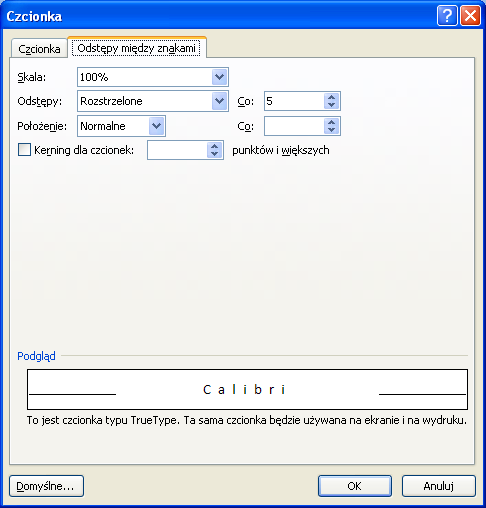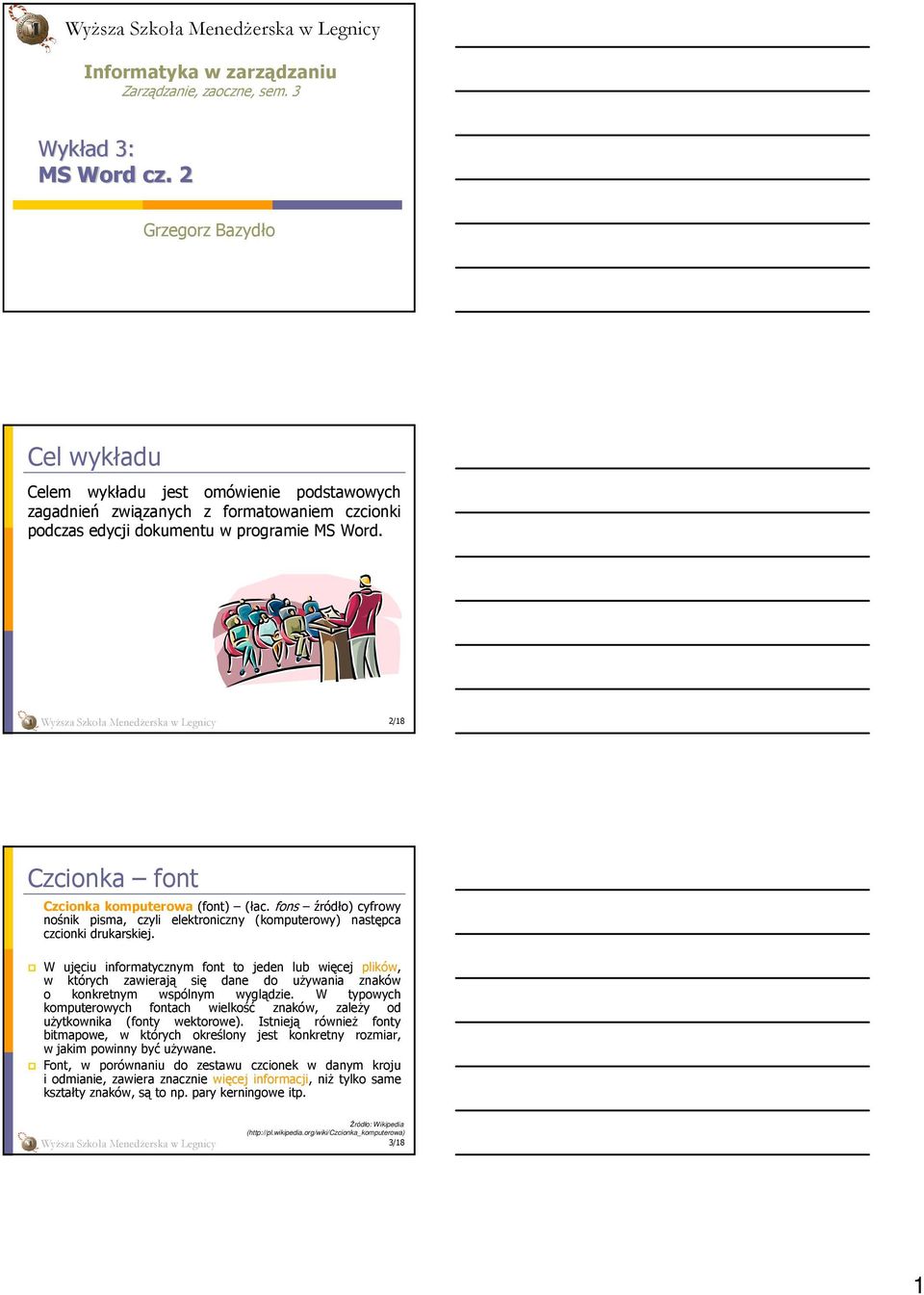
1 WyŜsza Szkoła MenedŜerska w Legnicy Informatyka w zarządzaniu Zarządzanie, zaoczne, sem. 3 Wykład 3: MS Word cz. 2 Grzegorz Bazydło Cel wykładu Celem wykładu jest omówienie podstawowych zagadnień związanych z formatowaniem czcionki podczas edycji dokumentu w programie MS Word. WyŜsza Szkoła MenedŜerska w Legnicy 2/18 Czcionka font Czcionka komputerowa (font) (łac. fons źródło) cyfrowy nośnik pisma, czyli elektroniczny (komputerowy) następca czcionki drukarskiej. W ujęciu informatycznym font to jeden lub więcej plików, w których zawierają się dane do uŝywania znaków o konkretnym wspólnym wyglądzie. W typowych komputerowych fontach wielkość znaków, zaleŝy od uŝytkownika (fonty wektorowe). Istnieją równieŝ fonty bitmapowe, w których określony jest konkretny rozmiar, w jakim powinny być uŝywane. Font, w porównaniu do zestawu czcionek w danym kroju i odmianie, zawiera znacznie więcej informacji, niŝ tylko same kształty znaków, są to np. pary kerningowe itp. Źródło: Wikipedia ( WyŜsza Szkoła MenedŜerska w Legnicy 3/18 1
2 Formaty fontów Type 1 Type 1 fonty postscriptowe Opracowanie formatu 1985r. Adobe (równolegle z PostScript) Pierwotnie zastosowane w komputerach firmy Apple (w tym czasie jako pierwsze weszły na rynek z graficznym środowiskiem pracy uŝytkownika oraz z przystosowaną do druku w tym trybie drukarką laserową). UmoŜliwiało to drukowanie dowolnych kształtów liter w płynnej skali wielkości. Znaki w T1 opisane są za pomocą krzywych Béziera trzeciego stopnia tworzących kontury kształtów znaków. Fonty T1 pozwalają przekształcać litery jako obiekty graficzne zaleŝnie od moŝliwości urządzeń drukujących oraz moŝliwości uŝywanego oprogramowania. WyŜsza Szkoła MenedŜerska w Legnicy 4/18 Krzywe Béziera trzeciego stopnia definiowane są poprzez ciągi punktów kontrolnych (węzłów). Krzywa Béziera trzeciego stopnia Źródło: Wikipedia ( WyŜsza Szkoła MenedŜerska w Legnicy 5/18 Formaty fontów TrueType format wymyślony przez Apple (antidotum na PostScript) Stosowany na komputerach Macintosh od 1991r. obecnie rozpowszechniony na wszystkich platformach komputerowych na równi z fontami Type 1. Znaki w TrueType opisane są za pomocą krzywych Béziera drugiego stopnia, jednak jest to format znacznie bardziej skomplikowany technicznie. Daje za to większe moŝliwości szczególnie pod względem jakości wyświetlania na ekranie monitora. WyŜsza Szkoła MenedŜerska w Legnicy 6/18 2
3 Formaty fontów OpenType uznawany za przyszłość formatów Wspólne dzieło Adobe i Microsoft Pierwsza aplikacja obsługująca format Adobe InDesign Kodowanie znaków w Unicode Zawierają szereg nowych funkcji niedostępnych w starszych formatach, jak np. znaki alternatywne, osadzanie krojów na stronach WWW (umoŝliwiające wyświetlanie ich w przeglądarce na komputerze, w którym tych znaków nie ma zainstalowanych). WyŜsza Szkoła MenedŜerska w Legnicy 7/18 Kodowanie znaków Kiedyś 1 font = 1 bajt = 256 znaków (bardzo mało) Odmiany regionalne dla fontów, np. wersji dla środkowej Europy, państw bałtyckich itd. Fonty greckie, cyrylica, znaki fonetyczne, piktogramy, symbole nut itd. z załoŝenia zawierały się od razu w odrębnych zestawach 256 znakowych Konieczność konwersji między róŝnymi standardami kodowania tych samych znaków Dzisiaj 1 font = 2 bajty = znaków (Unicode) Unicode tylko jeden standard kodowania znaków Unicode zestaw, w którym mieszczą się znaki ze wszystkich dotychczasowych stron kodowych WyŜsza Szkoła MenedŜerska w Legnicy 8/18 Krój pisma jeden z trzech podstawowych parametrów kaŝdej czcionki (pozostałe dwa to stopień i odmiana). NajwaŜniejszy element określający charakterystyczny wygląd i unikalność kaŝdej rodziny czcionek. Na świecie istnieje ogromna ilość fontów, ale większość z nich to drobne modyfikacje istniejących juŝ krojów. Kanon, do którego dorobiono całą rzeszę mniej lub bardziej udanych przeróbek, to kilkadziesiąt fontów. Krój pisma jest dziełem autorskim podlegającym ochronie prawnej. WyŜsza Szkoła MenedŜerska w Legnicy 9/18 3
4 Rodzaje krojów podział 1 Kroje jednoelementowe wszystkie kroje pisma, w których litery są zbudowane z kresek tej samej grubości. Tahoma Kroje dwuelementowe znaki w tych krojach mogą róŝnić się szerokością, np. wszystkie pionowe są innej szerokości niŝ poziome. WyŜsza Szkoła MenedŜerska w Legnicy 10/18 Rodzaje krojów podział 2 Pismo szeryfowe szeryfy to ozdobne, krótkie kreski stosowane w wielu krojach pisma do zwiększenia dekoracyjności danego fontu. Najczęściej są to poziome kreski będące stopkami liter, ale mogą występować równieŝ w innych miejscach znaków. Times New Roman Pismo bezszeryfowe fonty nie mające szeryfów (sans serif). Tahoma WyŜsza Szkoła MenedŜerska w Legnicy 11/18 Rodzaje krojów podział 3 Kroje stałe światła międzyliterowe (odstępy pomiędzy sąsiednimi literami) są stałe. Courier New Kroje proporcjonalne światła międzyliterowe są róŝne (zmieniają się proporcjonalnie). Garamond WyŜsza Szkoła MenedŜerska w Legnicy 12/18 4
5 Kerning regulowanie odległości pomiędzy konkretnymi parami znaków w danym kroju pisma i jego odmianie. Jest to jeden ze sposobów regulacji świateł międzyliterowych. Bez kerningu Z kerningiem Źródło: Wikipedia ( WyŜsza Szkoła MenedŜerska w Legnicy 13/18 Formatowanie czcionki wersja MS Word 2000 wersja MS Word 2007 WyŜsza Szkoła MenedŜerska w Legnicy 14/18 Formatowanie czcionki wersja MS Word 2000 wersja MS Word 2007 WyŜsza Szkoła MenedŜerska w Legnicy 15/18 5
6 Formatowanie czcionki wersja MS Word 2000 WyŜsza Szkoła MenedŜerska w Legnicy 16/18 Podsumowanie Czcionki komputerowe mogą występować w róŝnych formatach (Type 1, TrueType, OpenType) Obecnie standardem kodowania znaków jest Unicode Podstawowe parametry kaŝdej czcionki to: krój pisma, stopień i odmiana Przy tworzeniu dokumentów warto świadomie stosować róŝne kroje fontów (np. kroje jednoelementowe, szeryfowe, proporcjonalne). WyŜsza Szkoła MenedŜerska w Legnicy 17/18 6